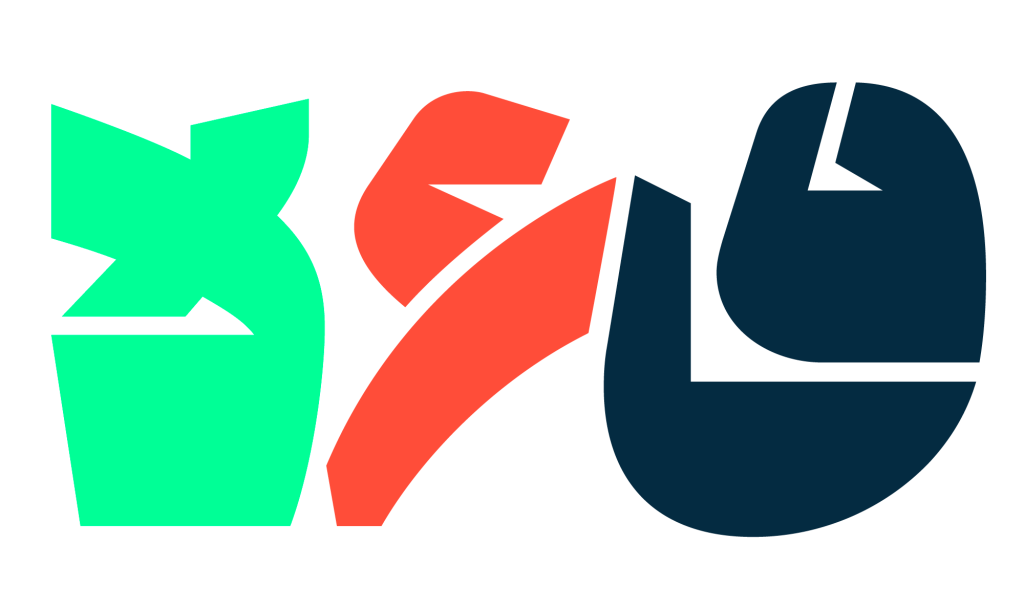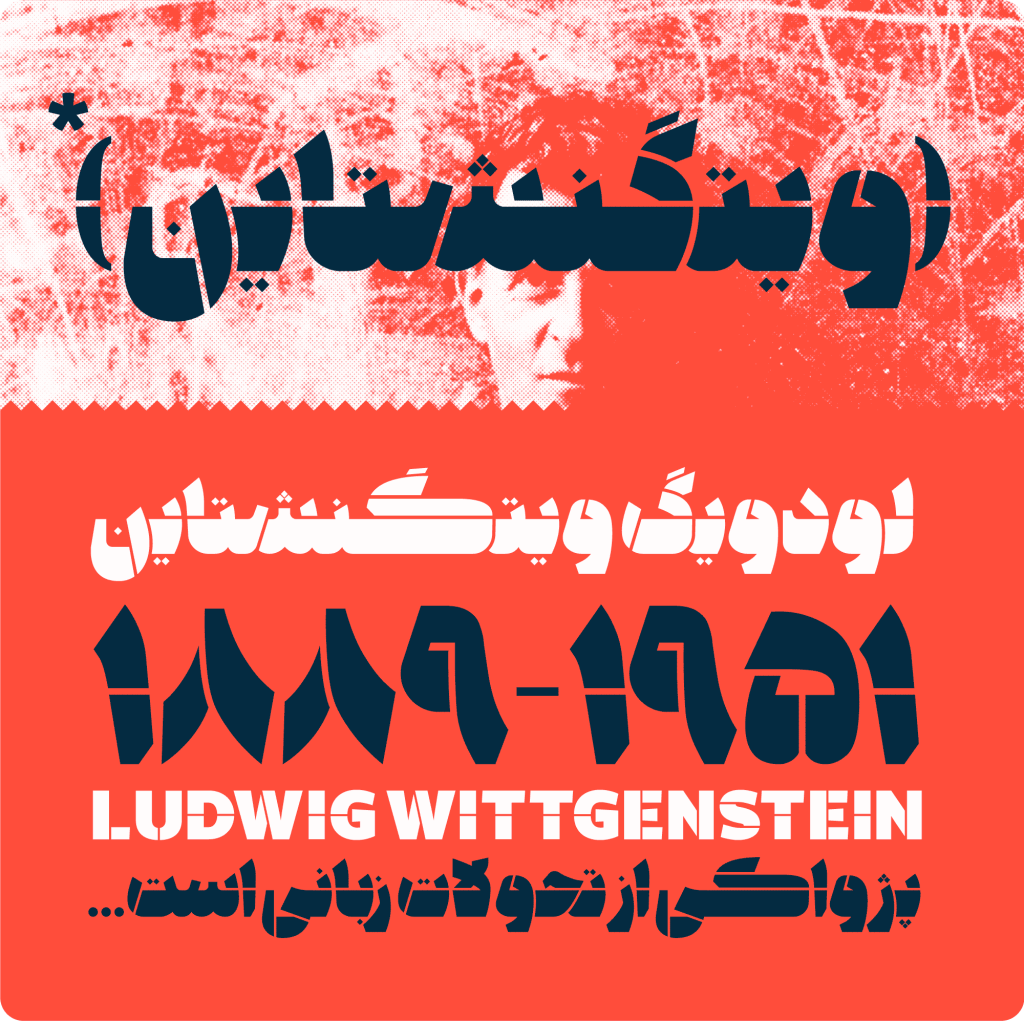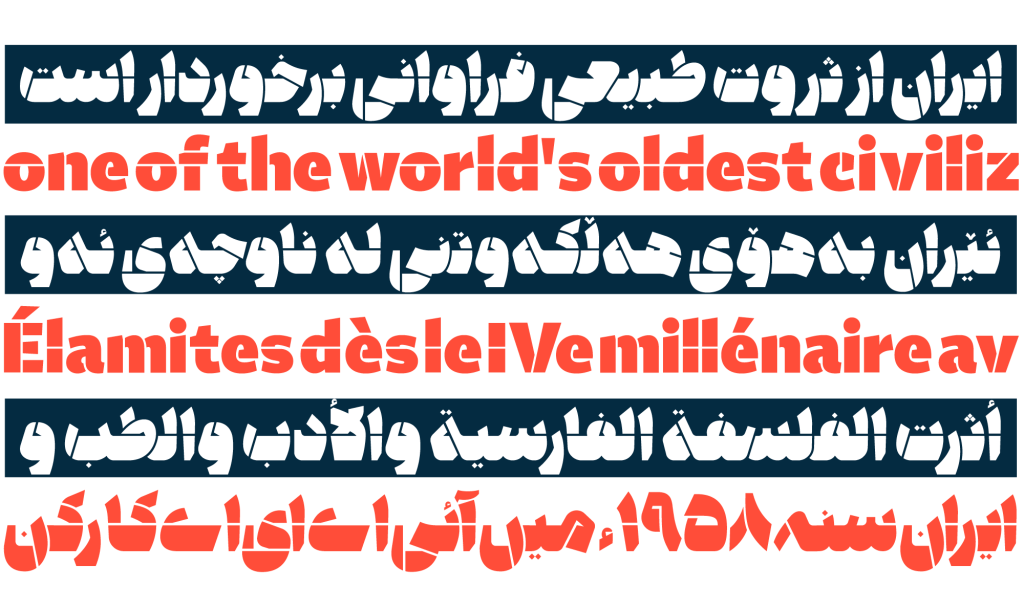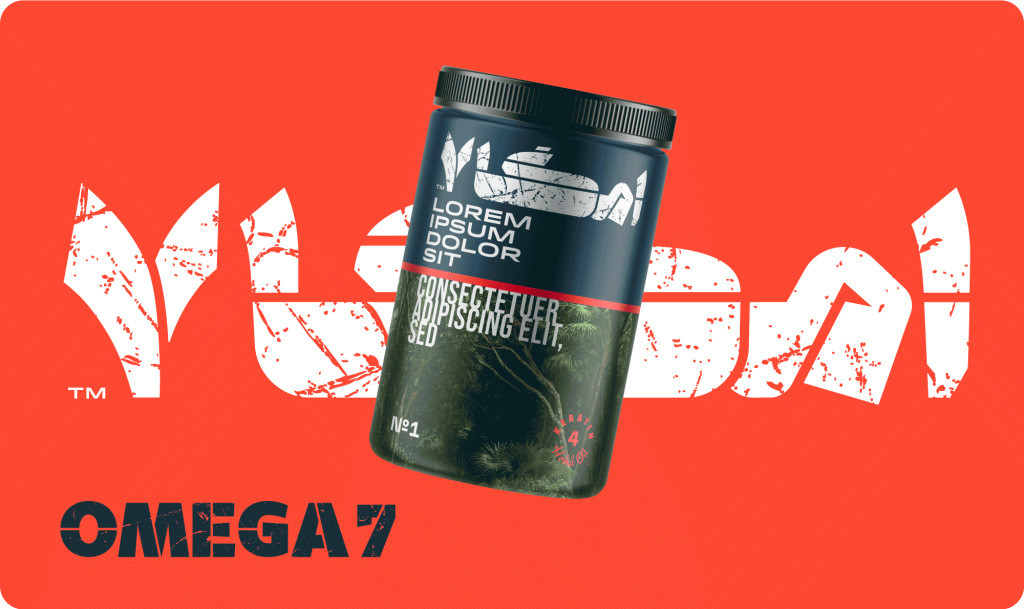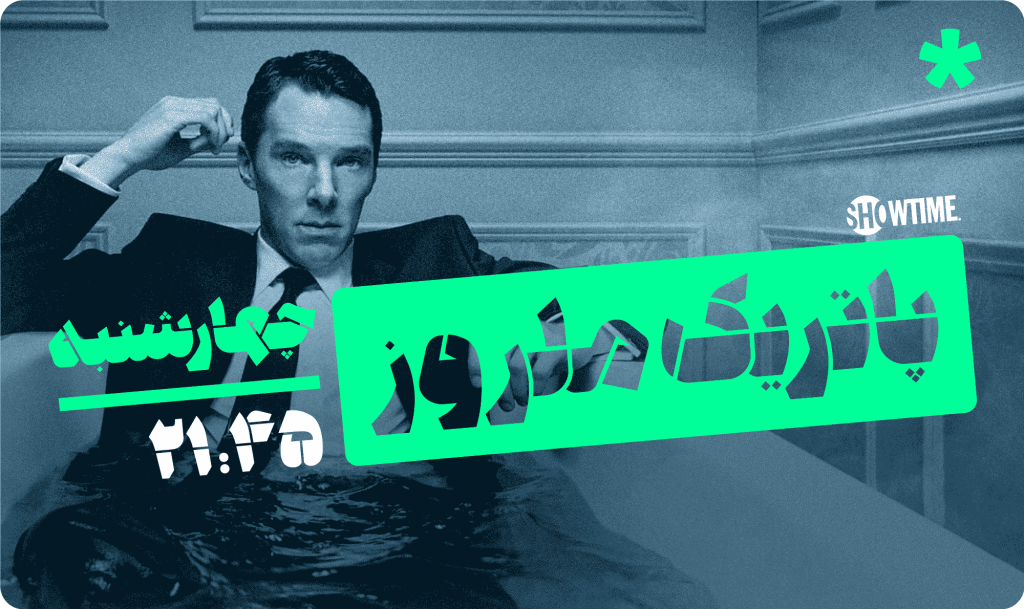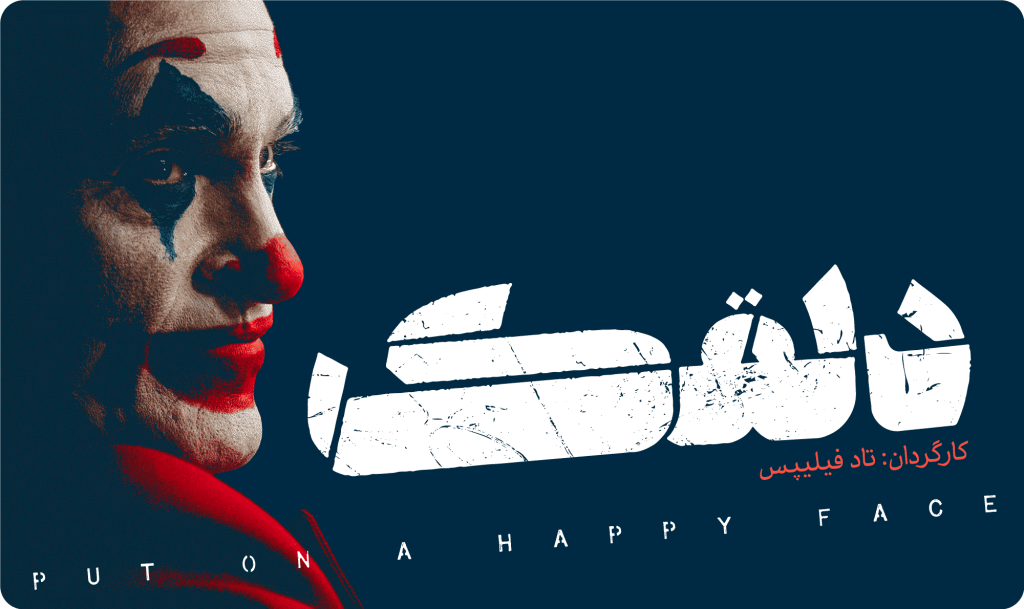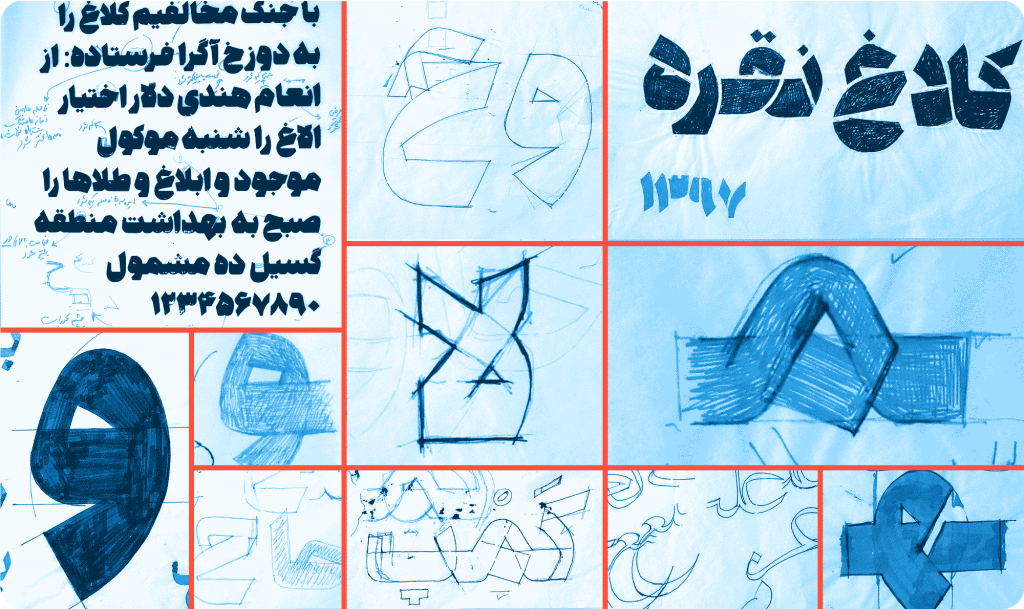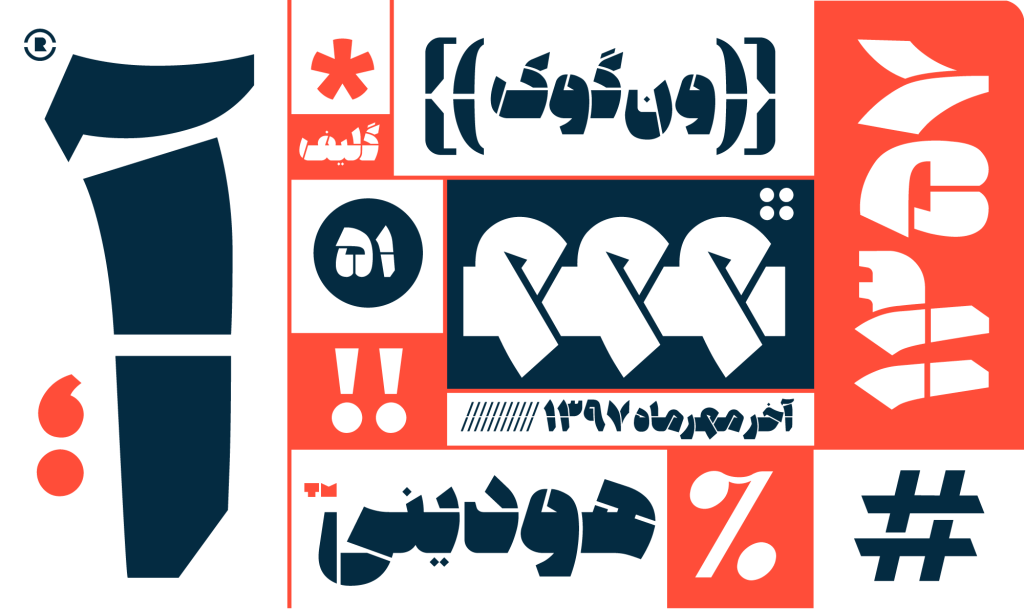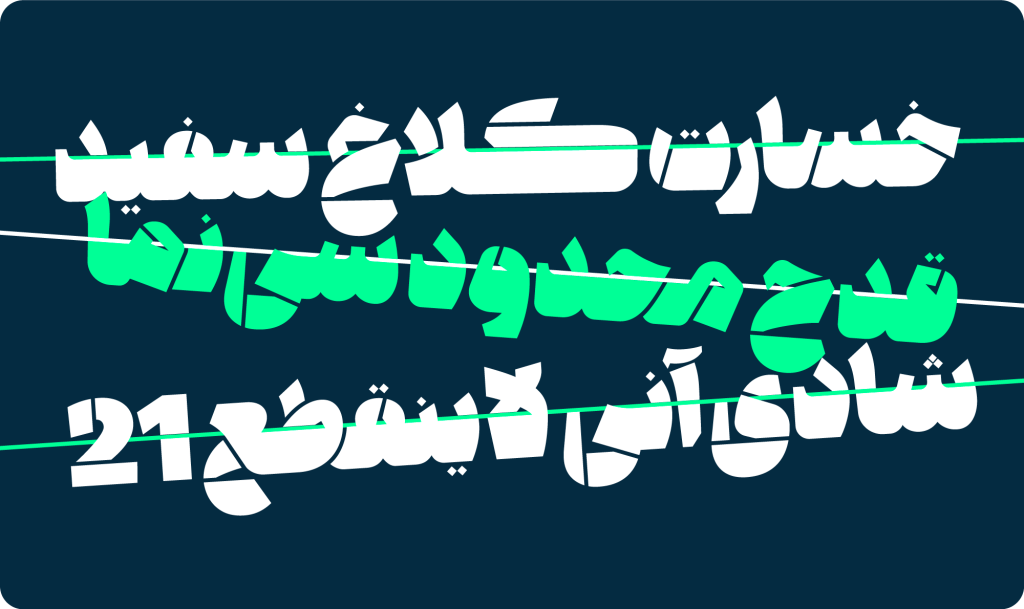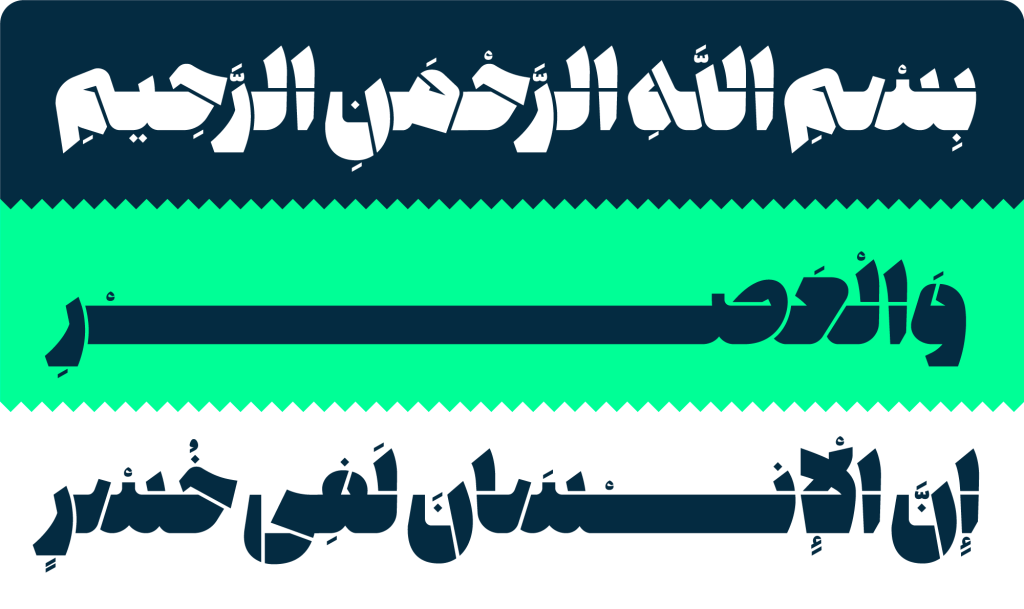
فونت 898استنسیل تایپ فیسی کلاسیک و مدرن با قدرت نمایشی بالا جهت جذب نگاه مخاطبین و بینندگان به متون کوتاه و عناوین و تیتر های خلاق و تبلیغاتی است. با ما همراه باشید تا این قلم زیبا را به شما عزیزان معرفی کنیم.
فونت 898استنسیل
فونت 898استنسیل قلمی مناسب با روحیه و حس و حالی کلاسیک و در عین حال مدرن الهام گرفته از خط خوشنویسی نسخ است. استنسیل تایپ فیسی با کنتراست سطحی قابل توجه می باشد. عرض ضخامت در بدنه اصلی آن نسبتا زیاد و جزء تایپ فیس های سنگین وزن و ضخیم به شمار می رود.
این قلم به همت فریدون نعمت پور و کامیاب جعفری طراحی گردیده است. فضاهای خالی در زوایای مختلف به این تایپ فیس حرکت و پویایی و رشد میدهد، چشم را درگیر میکند، و به نوعی قابلیت و ظرفیت آن پرورش داده است. استنسیل شخصیتی اصیل و سنتی دارد. در عین حال خود را در قالب های مدرن نیز قرار می دهد و سازگاری لازم را با آن فضا برقرار می کند.
پشتیبانی قلم استنسیل تنها به زبان فارسی خلاصه نمی شود . طراحی حروف و ترکیبات مورد نیاز برای سایر زبان ها سبب پشتیبانی این تایپ فیس از زبان های دیگری از جمله انگلیسی فرانسه عربی کردی اردو و … نیز گشته است.
از دیگر مشخصه های اصلی در این تایپ فیس اعداد می باشند. اعداد فارسی و انگلیسی که نقشی محوری را در طراحی تیتر ها و عناوین می توانند انجام دهند. نکته قابل توجه در استنسیل مقیاس اعراب و نقطه گذاری ها در مقایسه با سایز حروف و گلیف ها و … می باشد . که خود سبکی جدید و ایده ای نو می باشد.
این قلم زیر نظر استاد دامون خانجانزاده طراحی شده است . کاربرد استنسیل برای متون کوتاه و عناوین و تیتر های خلاق و جذاب برای انواع پوستر ها، مقالات جلد کتاب ها پست های وب سایت ها و شبکه های اجتماعی بیلبورد ها و … می باشد . در زیر تصاویری زیبا از این قلم برای شما عزیزان آماده شده است.